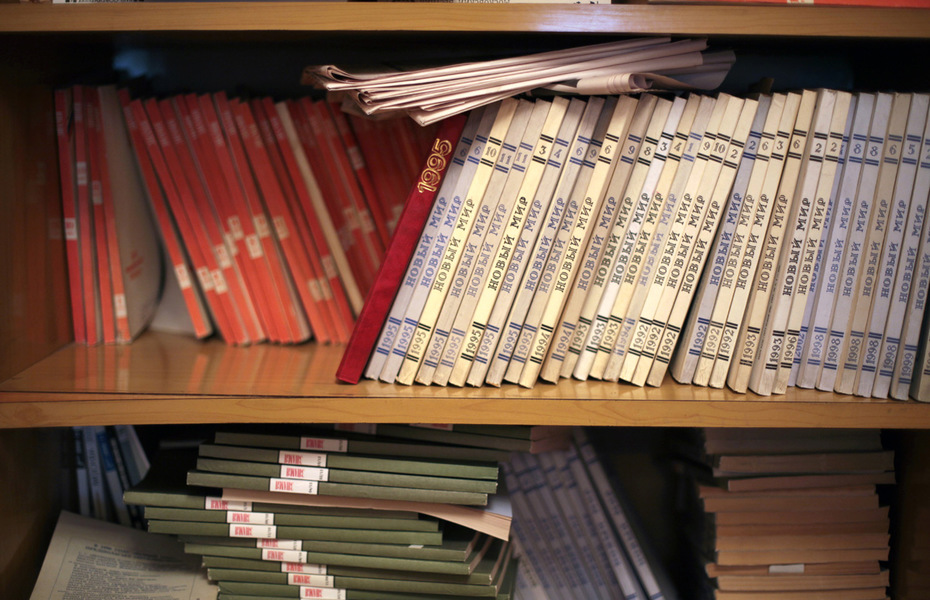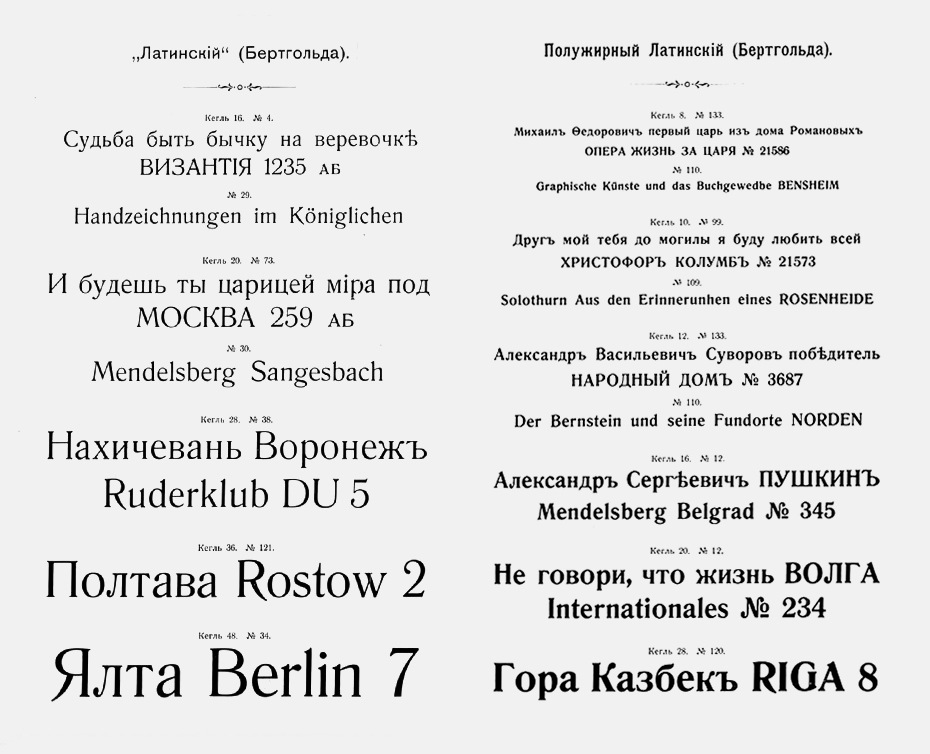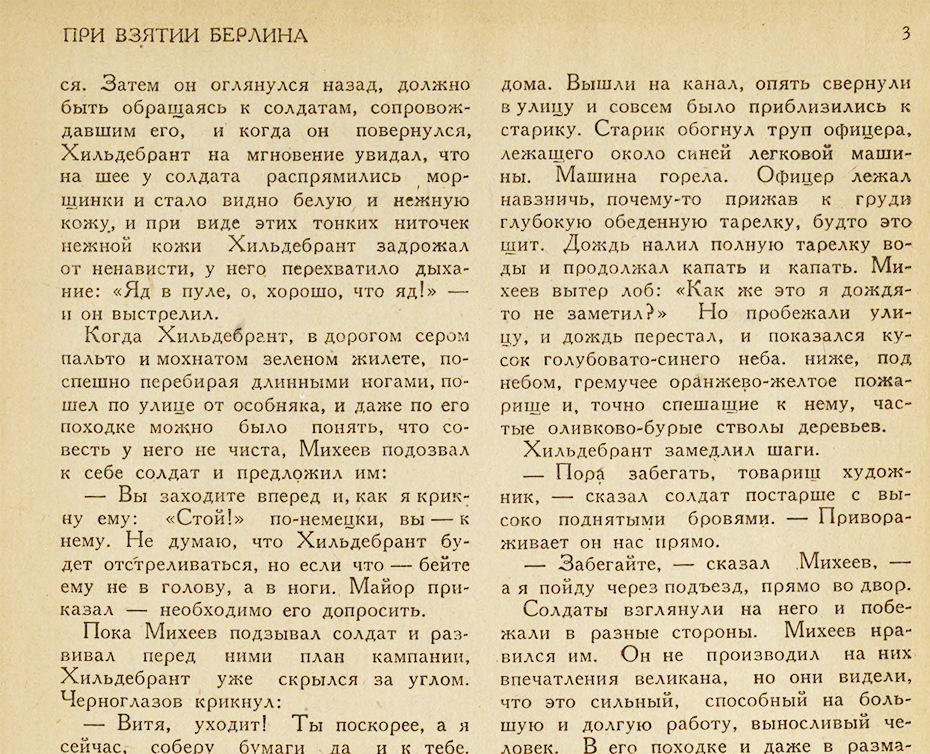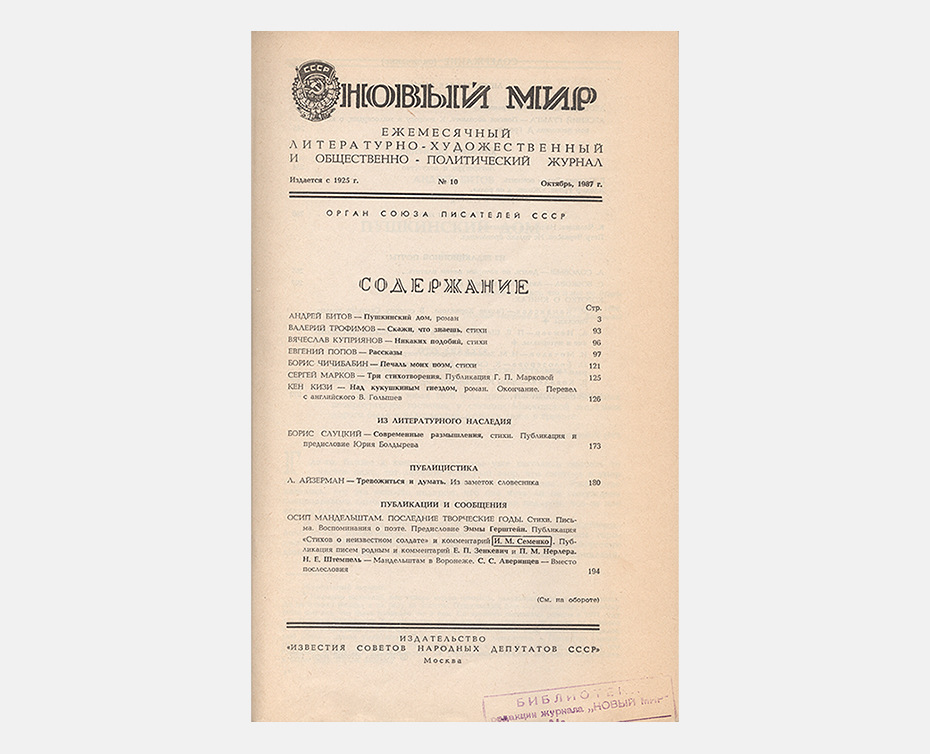
Беседа с главным редактором журнала «Новый мир» Андреем Василевским
Бе­се­да с глав­ным ре­дак­то­ром
жур­на­ла «Но­вый мир» Ан­дре­ем Ва­си­лев­ским
Раз­го­вор о ди­зай­не жур­на­ла нуж­но на­чать с то­го, что ди­зай­на в со­вре­мен­ном по­ни­ма­нии у не­го нет. Бо­лее то­го, лю­бое пе­ре­осмыс­ле­ние об­ли­ка из­да­ния рис­ку­ет раз­ру­шить при­выч­ный об­ра­з ле­ген­дар­но­го ли­те­ра­тур­но­го тол­стя­ка. Его ма­кет пре­дель­но прост и не­за­ме­тен. В жур­на­ле нет ил­лю­стра­ций. По­ло­са на­бо­ра, по­жа­луй, не­мно­гим от­ли­ча­ет­ся от «ру­ко­пи­сей», при­сы­ла­е­мых в ре­дак­цию: не­что усред­нён­ное, шрифт Times New Roman в 14 пунк­тов, по­лу­тор­ный ин­тер­вал, вы­ключ­ка на ши­ри­ну по­ло­сы. В вы­ход­ных дан­ных так и за­пи­са­но — «ком­пью­тер­ная вёрст­ка», не бо­лее. Но для не­сколь­ких по­ко­ле­ний чи­та­те­лей жур­нал остаёт­ся уз­на­ва­е­мым, зна­ко­вым. В 2005 го­ду пи­са­тель Дмит­рий Ба­виль­ский так пи­сал об этом фе­но­ме­не: «Ста­но­вой хре­бет. Ураль­ские го­ры. Не знаю, как объ­яс­нить. Ху­дож­ник и вер­сталь­щи­ки, ви­ди­мо, на­шли аб­со­лют со­еди­не­ния тек­ста и ма­те­ри­аль­но­го его во­пло­ще­ния. Имен­но тот шрифт. Шриф­ты. Имен­но этот за­го­ло­воч­ный ком­плекс. Да, та­кие вот за­глав­ные бук­вы, „фо­на­ри“ с лыч­кой по­сре­ди­не. Точ­но та­кая бук­ва „о“, или снос­ки, или пе­тит. Эй­дос бы­то­ва­ния про­из­ве­де­ния. Фе­но­ме­но­ло­ги­че­ская ре­дук­ция: текст как он есть. Го­лый, очи­щен­ный от все­го, так?» Мы по­пы­та­лись ра­зо­брать­ся с па­ра­док­сом вме­сте с глав­ным ре­дак­то­ром «Но­во­го ми­ра» Ан­дре­ем Ва­си­лев­ским.
Ан­дрей Ва­си­лев­ский ра­бо­та­ет в жур­на­ле с 1977 го­да. Во всех справ­ках мель­ка­ет фор­му­ла: «ку­рье­ром, зав­хо­зом, за­ве­ду­ю­щим биб­лио­те­кой, с 1990 го­да — от­вет­ствен­ный се­кре­тарь, с мар­та 1998 го­да — глав­ный ре­дак­тор». Ав­тор пя­ти книг сти­хов («Всё рав­но», 2009; «Ещё сти­хи», 2010; «Пло­хая фи­зи­ка», 2011; «Тро­фей­ное ору­жие», 2013; «Это хо­ро­шо», 2015). Ав­тор мно­же­ства кри­ти­че­ских ста­тей и ре­цен­зий, ве­ду­щий об­зо­ров пе­ри­о­ди­ки в «Но­вом ми­ре» с 1995 го­да. Ведёт се­ми­нар ли­те­ра­тур­но­го ма­стер­ства в Ли­те­ра­тур­ном ин­сти­ту­те им. Горь­ко­го в Моск­ве. Фо­то Ксе­нии Плот­ни­ко­вой.
В од­ном из ин­тер­вью вы ска­за­ли: «Я прин­ци­пи­аль­но об­ща­юсь с са­мы­ми раз­ны­ми ли­те­ра­тур­ны­ми людь­ми, в том чис­ле и с та­ки­ми, ко­то­рые са­ми друг дру­гу ру­ки не по­да­дут. Если есть на­пря­же­ние меж­ду тра­ди­ци­о­на­ли­ста­ми и мо­дер­ни­ста­ми, то это не моя вой­на». Это по­зи­ция глав­но­го ре­дак­то­ра «Но­во­го ми­ра» или че­ло­ве­ка, чи­та­те­ля?
Это и то и дру­гое. И «раз­ло­мы» про­хо­дят не толь­ко меж­ду услов­ны­ми тра­ди­ци­о­на­ли­ста­ми и мо­дер­ни­ста­ми, а по са­мым раз­ным ли­ни­ям, в том чис­ле и в сфе­ре лич­ных от­но­ше­ний. В «Но­вом ми­ре» ино­гда од­но­вре­мен­но пе­ча­та­ют­ся лю­ди, ко­то­рые мо­гут мир­но встре­тить­ся толь­ко на стра­ни­цах на­ше­го жур­на­ла.
При та­ком сти­ле­вом раз­но­об­ра­зии у жур­на­ла есть ка­кая-то по­зи­ция?
Я бы ска­зал, что жур­нал об­ла­да­ет куль­тур­ны­ми функ­ци­я­ми. Идео­ло­ги­че­ские, по­ли­ти­че­ские по­зи­ции име­ют­ся у «На­ше­го со­вре­мен­ни­ка» или «Моск­вы», а у та­ких жур­на­лов, как «Но­вый мир», «Ок­тябрь», «Зна­мя» или «Друж­ба на­ро­дов», — имен­но куль­тур­ные функ­ции, во мно­гом сов­па­да­ю­щие. Во-пер­вых, это со­хра­не­ние жан­ро­во­го раз­но­об­ра­зия ли­те­ра­ту­ры. Если мы го­во­рим о бу­ма­ге, а не се­ти, то кон­ку­рен­ция с из­да­тель­ства­ми у нас лишь в од­ном сег­мен­те — это ро­ман, по­сколь­ку се­го­дня ре­аль­ной ком­мер­че­ской цен­но­стью об­ла­да­ет толь­ко этот жанр. Ку­да пой­дёт не ро­ма­нист, а че­ло­век, на­пи­сав­ший не­боль­шую по­весть? В жур­нал. То же от­но­сит­ся и к ав­то­рам рас­ска­зов, и, са­мо со­бой, к по­этам. Ав­то­ры боль­ших ана­ли­ти­че­ских ре­цен­зий не­га­зет­но­го ти­па то­же пой­дут в жур­нал. Та­ким об­ра­зом, тол­стые жур­на­лы — это ков­чег ма­лых жан­ров. Дру­гой важ­ный мо­мент — мы про­да­ём не ав­то­ров, не про­из­ве­де­ния, а жур­нал как це­лое. Мы не оце­ни­ва­ем каж­до­го ав­то­ра с ком­мер­че­ской точ­ки зре­ния, в от­ли­чие от мно­гих из­да­те­лей.
Куль­тур­ная функ­ция — это от­вет­ствен­ность, а мо­жет быть, и на­сто­я­щее бре­мя. Вы не ощу­ща­е­те, что «мат­ри­ца» глав­но­го ли­те­ра­тур­но­го жур­на­ла, за­ло­жен­ная ещё в го­ды осно­ва­ния «Но­во­го ми­ра» в 20-е, взя­ла над ва­ми верх? Не бы­ло же­ла­ния в 1990-е го­ды, в по­ру все­воз­мож­ных со­блаз­нов, рез­ко сме­нить курс? Стать свет­ским ли­те­ра­тур­ным жур­на­лом, впу­стить в жур­нал гра­фи­ку, фо­то, ти­по­гра­фи­че­ское раз­но­об­ра­зие?
А что та­кое «свет­ский жур­нал», по-ва­ше­му?
«Нью-Йор­кер», услов­но го­во­ря.
При­шлось бы за­крыть этот жур­нал и под тем же на­зва­ни­ем на­чать со­вер­шен­но дру­гой, по­ни­ма­е­те? Но сна­ча­ла — за­крыть этот. Че­го мы все как раз пы­та­ем­ся из­бе­жать. Нам важ­но со­хра­нить фор­мат.
То­гда мой во­прос о сме­не оформ­ле­ния жур­на­ла, в об­щем-то, не име­ет смыс­ла.
Нет, по­че­му? Дру­гие жур­на­лы, «Ино­стран­ная ли­те­ра­ту­ра» на­при­мер, ме­ня­ли свой гра­фи­че­ский об­лик, при­чём это ка­са­лось и шап­ки, и ма­ке­та, и шриф­тов. «Не­ва» сме­ни­ла по­ли­гра­фи­че­ский фор­мат. На об­лож­ку «Ок­тя­бря» про­ник­ла ил­лю­стра­ция. «Зна­мя», «Друж­ба на­ро­дов» чуть-чуть ме­ня­ли цве­то­вую гам­му. Они де­ла­ли это край­не осто­рож­но, в де­та­лях. Мы един­ствен­ный жур­нал, ко­то­рый прак­ти­че­ски не из­ме­нил ни­че­го. Если что-то и ме­ня­лось — это бы­ли вы­ну­жден­ные ме­ры. На­ша зна­ко­вая ны­не си­няя об­лож­ка пе­ча­та­лась в со­вет­ское вре­мя на кра­шен­ной в мас­се бу­ма­ге, с двух сто­рон, это бы­ли зри­мая фак­ту­ра и цвет. А по­том та­кую бу­ма­гу пре­кра­ти­ли вы­пус­кать. И мы вы­ну­жде­ны бы­ли пе­рей­ти на ис­кус­ствен­ную за­пе­чат­ку. Ко­неч­но, это ухуд­ши­ло внеш­ний вид, об­лож­ка про­из­во­дит дру­гое впе­чат­ле­ние.
Что же до «но­во­мир­ско­го» шриф­та, то мы его со­хра­ни­ли — это ка­са­ет­ся на­зва­ния руб­рик, со­дер­жа­ния и про­че­го. Но по­ни­ма­е­те, в чём де­ло, наш жур­нал в ка­кой-то сте­пе­ни ими­ти­ру­ет тра­ди­ци­о­на­лизм. И ча­стью этой ими­та­ции яв­ля­ет­ся его оформ­ле­ние. При­том что на са­мом де­ле вну­три-то, со­дер­жа­тель­но, он ме­ня­ет­ся. Не ре­во­лю­ци­он­ным об­ра­зом, мед­лен­но, но не­уклон­но. Не­из­мен­ный ас­ке­тич­ный ди­зайн «Но­во­го ми­ра» под­чёр­ки­ва­ет пре­ем­ствен­ность, кон­сер­ва­тизм. От­ча­сти это чест­ная бед­ность. Будь у нас воз­мож­ность, я с удо­воль­стви­ем взял бы для об­лож­ки бу­ма­гу дру­го­го сор­та и ка­че­ства, бо­лее при­ят­ную на ощупь, бо­лее со­лид­ную… Но что ка­са­ет­ся все­го гра­фи­че­ско­го об­ра­за — я ду­маю, его ни в ко­ем слу­чае не сто­ит ме­нять.
«Но­вый мир» был осно­ван в 1925 го­ду. Кар­на­валь­ное, слож­ное вре­мя — и в ли­те­ра­тур­ном про­цес­се, где од­но­вре­мен­но ра­бо­та­ет мно­же­ство ор­га­ни­за­ций и раз­но­стиль­ных групп пи­са­те­лей, и в жиз­ни стра­ны. В ка­ких усло­ви­ях он за­ро­ждал­ся, в ка­кой ти­по­гра­фии пе­ча­тал­ся, кто участ­во­вал в его оформ­ле­нии?
Важ­ный мо­мент — «Но­вый мир» был со­здан не пи­са­те­ля­ми и не как ор­ган ка­ко­го-то пи­са­тель­ско­го со­ю­за. Это был го­су­дар­ствен­ный ли­те­ра­тур­ный жур­нал при из­да­тель­стве «Из­ве­стия», со­здан­ный со­вет­ским пра­ви­тель­ством. С 1925 го­да до на­ча­ла 1990-х жур­нал вы­хо­дил в из­да­тель­стве «Из­ве­стия». На мо­ей па­мя­ти — а я ра­бо­таю в жур­на­ле с се­ре­ди­ны 1970-х — он все­гда был струк­тур­ным под­раз­де­ле­ни­ем из­да­тель­ства. То есть жур­нал не был от­дель­ным юр­ли­цом, не об­ла­дал ни фи­нан­со­вой, ни хо­зяй­ствен­ной са­мо­сто­я­тель­но­стью, так же как и мас­са дру­гих из­да­ний, ко­то­рые «Из­ве­стия» вы­пус­ка­ло. Над жур­на­лом ра­бо­та­ли на­бор­щи­ки и мет­ран­па­жи это­го из­да­тель­ства. Бух­гал­те­рия и от­дел кад­ров — то­же в из­да­тель­стве. Фра­за о том, что жур­нал — «Ор­ган Со­ю­за пи­са­те­лей СССР», по­яви­лась толь­ко с кон­ца 1940-х. Впро­чем, фи­нан­со­во и тех­ни­че­ски по­сле это­го ни­че­го не из­ме­ни­лось. Соб­ствен­но, по­то­му и раз­рыв с Со­ю­зом пи­са­те­лей про­шёл до­ста­точ­но без­бо­лез­нен­но. И с «Из­ве­сти­я­ми» то­гда же мы ра­зо­шлись мир­но.
Ка­кие сей­час у жур­на­ла тех­ни­че­ские па­ра­мет­ры — ти­раж, под­пис­ка?
К со­жа­ле­нию, ти­ра­жи жур­на­ла не­дав­но рез­ко упа­ли и се­го­дня со­став­ля­ют 2500 эк­зем­пля­ров. Хо­тя ещё два-три го­да на­зад, су­дя по дан­ным Книж­ной па­ла­ты, со­кра­ще­ние на­ше про­ис­хо­ди­ло при­мер­но те­ми же тем­па­ми, что и так на­зы­ва­е­мый «сред­ний книж­ный ти­раж» (4000–5000 эк­зем­пля­ров). Это бы­ло не слу­чай­ное сов­па­де­ние, ведь жур­на­лы та­ко­го ти­па по при­ро­де сво­ей близ­ки кни­ге, в от­ли­чие от цвет­но­го еже­не­дель­ни­ка или га­зе­ты.
В 1990 го­ду ти­раж жур­на­ла пре­вы­сил циф­ру в не­сколь­ко мил­ли­о­нов. Рас­ска­жи­те об этом мо­мен­те.
Это бы­ла сво­е­го ро­да па­то­ло­гия. В ту ис­то­ри­че­скую ми­ну­ту ти­раж по под­пис­ке до­стиг уров­ня 2 700 000 эк­зем­пля­ров. При этом рын­ка бу­ма­ги ещё не бы­ло, эко­но­ми­ка оста­ва­лась ад­ми­ни­стра­тив­но-рас­пре­де­ли­тель­ной. Мы не вы­пу­сти­ли три но­ме­ра — с ок­тя­бря по де­кабрь — про­сто по­то­му, что в из­да­тель­стве «Из­ве­стия» за­кон­чи­лась бу­ма­га, а ку­пить бы­ло не­воз­мож­но.
Не­сколь­ко лет на­зад у жур­на­ла по­явил­ся свой сайт, где мож­но ку­пить све­жий но­мер «Но­во­го ми­ра» в раз­лич­ных фор­ма­тах. Вы от­сле­жи­ва­е­те ста­ти­сти­ку сай­та?
Мы не обо­льща­лись, что там бу­дут зна­чи­мые для на­ше­го бюд­же­та про­да­жи. Так и ока­за­лось: они аб­со­лют­но сим­во­ли­че­ские. Но нам бы­ло важ­но со­здать тех­ни­че­ский ме­ха­низм про­да­жи PDF-вер­сии (и дру­гих фор­ма­тов) c по­мо­щью раз­лич­ных пла­тёж­ных си­стем. Мы вы­де­ли­ли не­кую сум­му де­нег, ко­то­рую так и не оку­пи­ли, но это нас не вол­ну­ет. Про­сто бу­ду­щее жур­на­ла всё рав­но свя­за­но с чем-то по­доб­ным. Во­об­ще, в ин­тер­не­те у нас (и у дру­гих жур­на­лов) очень боль­шой про­цент чи­та­те­лей в «Жур­наль­ном за­ле», при­чём я бы ска­зал, что на­род в «Жур­наль­ный зал» про­сто ва­лит. Глеб Пав­лов­ский, бла­го­да­ря ко­то­ро­му пор­тал су­ще­ству­ет, да­же вы­ну­жден был за­ку­пать до­пол­ни­тель­ные сер­ве­ра, по­то­му что сайт пе­ре­стал вы­дер­жи­вать на­груз­ки.
С чем вы свя­зы­ва­е­те та­кой боль­шой рост чи­та­те­лей в «Жур­наль­ном за­ле»?
По­то­му что это бес­плат­но и все жур­на­лы в од­ном ме­сте. А наш сайт — это ещё и за­пас­ной аэро­дром на слу­чай, если, не дай бог, рух­нет «Жур­наль­ный зал».
Игорь Са­ве­льев
Пи­са­тель, жур­на­лист
Со­вет­ская ис­то­рия «Но­во­го ми­ра» пе­ре­ска­за­на сот­ни раз (а са­ми жур­на­лы в го­лу­бой об­лож­ке — не­пре­мен­ный ре­кви­зит филь­мов о про­шлом). Ин­те­рес­нее дру­гое — жизнь по­сле «кру­ше­ния ан­тич­но­сти», ко­гда по­доб­ным ко­лос­сам бы­ли уго­то­ва­ны три ва­ри­ан­та судь­бы. Пер­вый — смерть, вто­рой — ко­ма, то есть фи­зи­че­ское су­ще­ство­ва­ние с пол­ной уте­рей преж­не­го зна­че­ния (здесь мож­но вспо­мнить МХАТ име­ни Горь­ко­го в пом­пез­ном зда­нии на Твер­ском буль­ва­ре, а из ли­те­ра­тур­ных жур­на­лов — «Юность»), тре­тий, са­мый слад­кий в гла­мур­но-сы­тую эпо­ху ну­ле­вых, — под­хват по­лу­мёрт­вых (или ка­кое-то вре­мя уже быв­ших мёрт­вы­ми) брен­дов по­сто­рон­ни­ми, но­вы­ми ко­ман­да­ми с рас­крут­кой но­вых, кре­а­тив­ных и де­неж­ных про­ек­тов, ко­то­рым на­сле­дие нуж­но имен­но в ка­че­стве брен­дов (и тут де­ло шриф­та­ми, эм­бле­ма­ми и про­чей ви­зу­ал­кой обыч­но и огра­ни­чи­ва­ет­ся).
Уни­каль­ность «Но­во­го ми­ра» в том, что он не пошёл ни по од­но­му из этих пу­тей. В ли­те­ра­тур­ном про­цес­се он остал­ся тем же «глав­ным жур­на­лом» — че­рез не­го про­хо­дит основ­ной кор­пус тех тек­стов, ко­то­рые мы по­том ви­дим на пол­ках ма­га­зи­нов в яр­ких об­лож­ках «Экс­мо» или «АСТ» и в пре­ми­аль­ных шорт-ли­стах. От­крыв све­жий но­мер жур­на­ла, че­ло­век, чьи ин­те­ре­сы ле­жат в сфе­ре мас­со­во­го чте­ния, дей­стви­тель­но, встре­тит не ­мно­го зна­ко­мых имён — но толь­ко по­то­му, что со­вре­мен­ная рус­ская ли­те­ра­ту­ра уже не яв­ля­ет­ся мас­со­вой (а те, ко­му всё-та­ки нуж­ны в ка­че­стве кри­те­рия гром­кие име­на, об­на­ру­жат в под­шив­ках по­след­них лет и Улиц­кую, и Аку­ни­на, и Бы­ко­ва, и За­ха­ра При­ле­пи­на, и мно­гих дру­гих вплоть до Сол­же­ни­цы­на, ко­то­рый оста­вал­ся ве­рен «Но­во­му ми­ру» до кон­ца сво­их дней).
На­ко­нец, «Но­вый мир» не про­шёл ре­брен­динг и не был под­хва­чен но­вой ко­ман­дой, как ка­кое-ни­будь име­ни­тое чу­че­ло, — нет, тем и хо­ро­ша го­лу­бая об­лож­ка и при­ме­ча­тель­ный «но­во­мир­ский» шрифт, что они не вы­пя­чи­ва­лись в но­вей­шей ис­то­рии, не пре­вра­ща­лись в фе­тиш и не свер­ка­ли но­вы­ми крас­ка­ми, как фа­сад не­дав­но от­стро­ен­ной го­сти­ни­цы «Моск­ва». «Но­вый мир» не аутен­ти­чен, он тот же, и в этом его уни­каль­ность. К че­му я это? К то­му, что ны­не жи­ву­щих (а не до­жи­ва­ю­щих) па­мят­ни­ков кон­струк­ти­виз­ма оста­лось все­го два. Гранё­ный ста­кан и об­лож­ка «Но­во­го ми­ра».
Вам не ка­жет­ся, что элек­трон­ная книж­ная ре­во­лю­ция так и не на­сту­пи­ла? Текст не по­ки­нул бу­ма­гу, не­смот­ря на огром­ное ко­ли­че­ство раз­го­во­ров за по­след­ние пять-­де­сять лет.
Зна­е­те, я уже не по­мню, ко­гда в по­след­ний раз дер­жал в ру­ках на­сто­я­щую га­зе­ту. Ко­гда я бе­ру её в ру­ки, пер­вое, что я ду­маю, — ка­кая она не­нуж­ная, ка­кая она бес­смыс­лен­ная. Что с ней де­лать, как ей поль­зо­вать­ся? У ме­ня атро­фи­ро­ва­лись преж­ние на­вы­ки ра­бо­ты с бу­маж­ной га­зе­той — пол­но­стью. Я не мо­гу её чи­тать. Вме­сто это­го я каж­дое утро са­жусь за ком­пью­тер, от­кры­ваю за­клад­ки основ­ных га­зет и чи­таю на экра­не «Из­ве­стия», «Ком­мер­сант» и так да­лее. И ни­че­го дру­го­го мне не нуж­но. То же мо­гу ска­зать и про жур­на­лы, и про цвет­ные еже­не­дель­ни­ки — я всё чи­таю на их сай­тах. Я и тол­стые жур­на­лы ред­ко в ру­ках дер­жу! При этом мы ча­сто пе­ре­се­ка­ем­ся с глав­ны­ми ре­дак­то­ра­ми дру­же­ствен­ных жур­на­лов, об­ща­ем­ся, но чи­таю я их из­да­ния в «Жур­наль­ном за­ле».
Но сна­ча­ла по­яв­ля­ет­ся бу­маж­ная вер­сия, и лишь по­том её вы­кла­ды­ва­ют на сайт.
Ну и что? Воз­мож­ность ме­нять раз­мер шриф­та на экра­не (вы в оч­ках, пой­мё­те ме­ня) — это та­кая дра­го­цен­ность, ко­то­рую ни­что не по­бе­дит.
У ме­ня в бра­у­зе­ре по умол­ча­нию мас­штаб 150%.
Вот-вот. Это ка­са­ет­ся и книг — за по­след­нее вре­мя я пол­но­стью пе­ре­клю­чил­ся на ри­де­ры. И это про­цесс по­все­мест­ный… Зна­е­те, ко­ми­тет пре­мии «Боль­шая кни­га» в пер­вые го­ды сво­е­го су­ще­ство­ва­ния при­во­зил мне ящик книг фи­на­ли­стов. А в ка­кой-то год они спра­ши­ва­ют: ни­че­го, если мы вам фле­шеч­ку под­ве­зём? Ну да­вай­те, го­во­рю, па­ке­тик с фле­шеч­кой…
А вас не раз­дра­жа­ет, что если вы чи­та­е­те не про­сто ро­ман, а вещь с ком­мен­та­ри­я­ми в кон­це и мно­же­ством сно­сок, то чи­сто фи­зи­че­ски не­воз­мож­но бы­стро пе­ре­ме­стить­ся к при­ме­ча­нию?
Есть про­сто дур­но под­го­тов­лен­ные фор­ма­ты элек­трон­ных вер­сий книг. Это, ко­неч­но, раз­дра­жа­ет. В не­ко­то­рых фор­ма­тах мож­но пры­гать ту­да-сю­да, к снос­кам и обрат­но.
И всё же ка­ки­ми сло­ва­ми вы опи­са­ли бы со­вре­мен­ный об­лик «Но­во­го ми­ра»?
Ум­ные сло­ва для ум­ных лю­дей, и ни­че­го боль­ше. Это от­но­сит­ся ко все­му пе­ри­о­ду су­ще­ство­ва­ния жур­на­ла. Ни ил­лю­стра­ций, ни гром­кой ти­по­гра­фи­ки, ни­че­го. И соб­ствен­но, он всем сво­им ви­дом го­во­рит: здесь нет ни­че­го лёг­ко­го, ни­че­го пред­на­зна­чен­но­го для рас­смат­ри­ва­ния, а толь­ко текст, ко­то­рый нуж­но мед­лен­но, вни­ма­тель­но чи­тать.